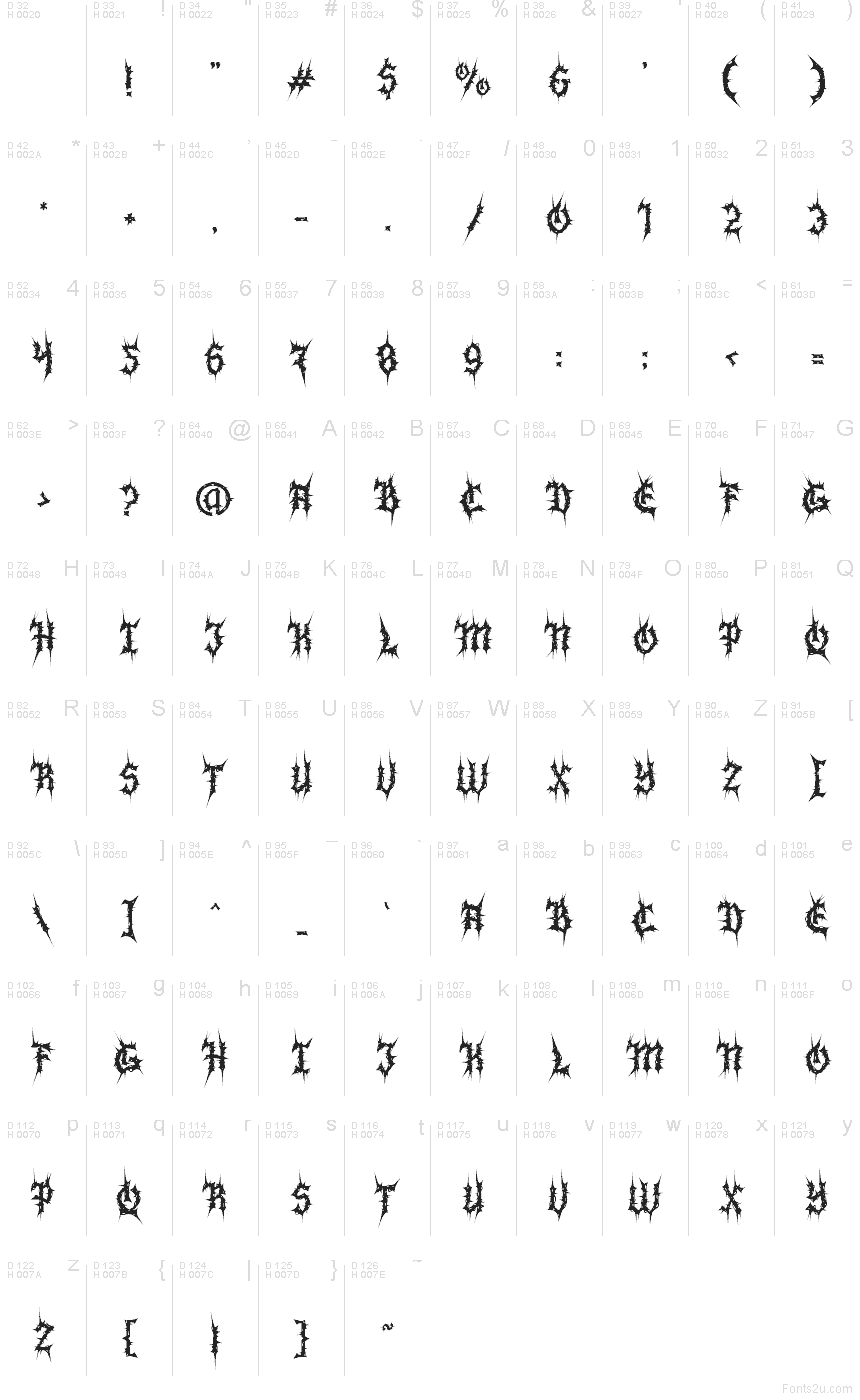
Silent Scream di Putracetol Studio è un font moderno in maiuscolo, in stile gotico con un'anima horror. Le lettere sembrano graffiate e impigliate tra le spine, con punte affilate che si protendono verso l'esterno e intagli stretti nelle forme; il risultato è un design che ricorda più il metallo graffiato o i rovi che una tradizionale blackletter.
È una scelta perfetta per poster horror, merchandising metal, titoli di giochi, grafiche per eventi di Halloween e anteprime di streaming dove servono poche parole con una silhouette tesa e frastagliata. Trattandosi di un font gratuito, è ideale anche per copertine, esperimenti su loghi e marchi brevi che possono sfruttare quei contorni spinosi senza bisogno di molto testo.